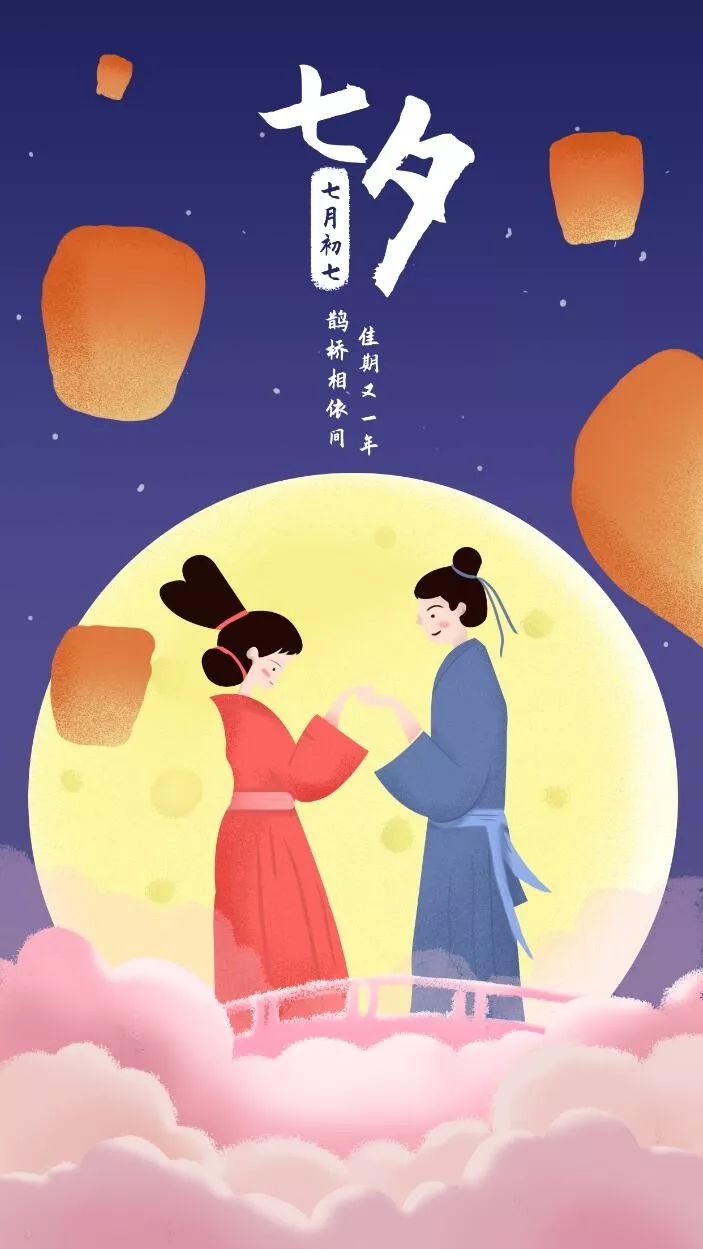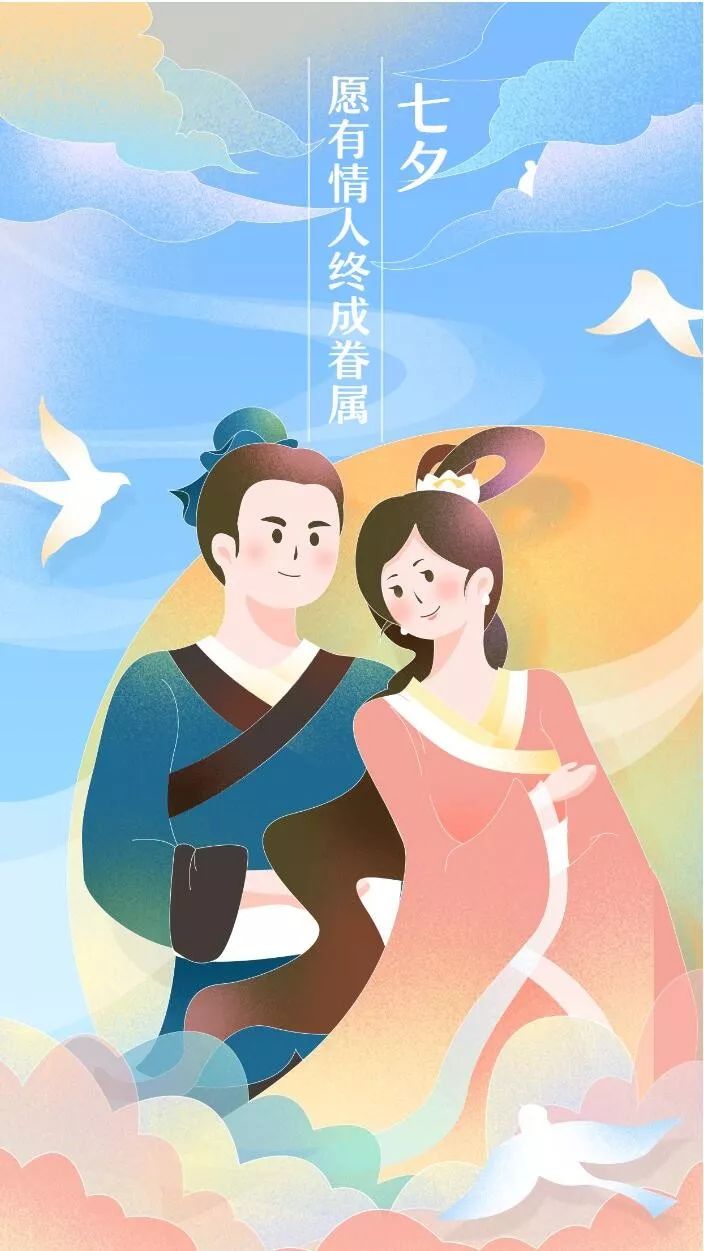
这个七夕,字体要少虐狗多走心~
后天就是七夕了,多少人又开始虐狗的节奏~
可我们都忘了七夕是中国的情人节,源自一个美好的故事,它不应该是浮于表面的甜蜜,而是内心深处的珍惜和思念,所以今天柚子就帮你们整一整!
古风寄情
既然是起源于中国的神话,传统的书法、古典字体自然必不可少,将时光带回3000多年前……
▲庞门正道粗书体
温暖有爱
除了中国风,看起来圆润、温暖的字体,也能还原牛郎织女的美好爱情……
▲汉仪润圆